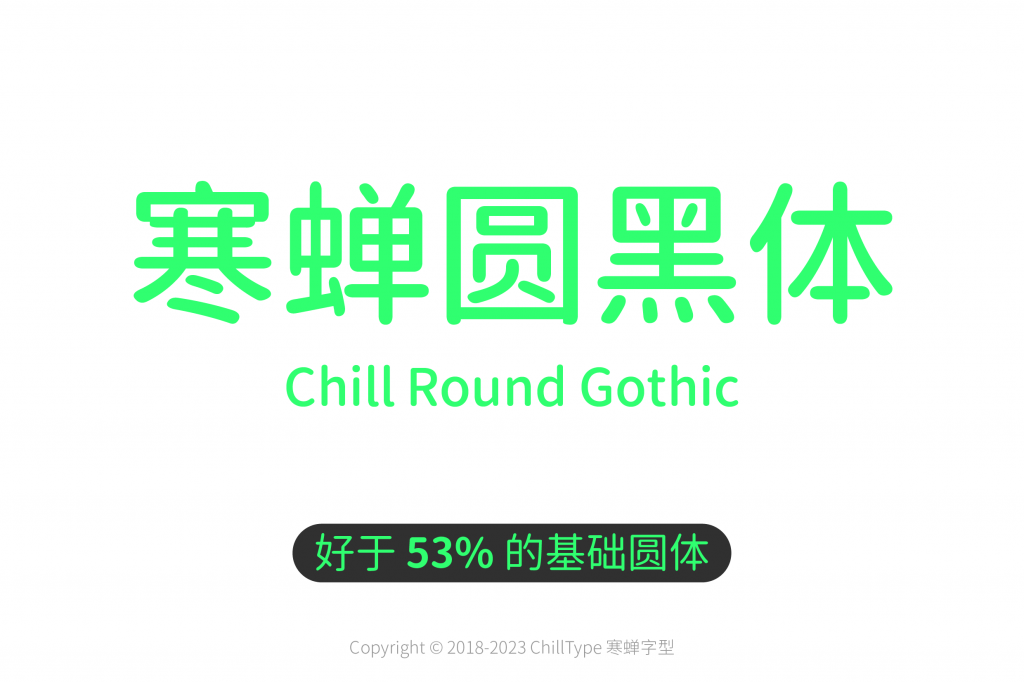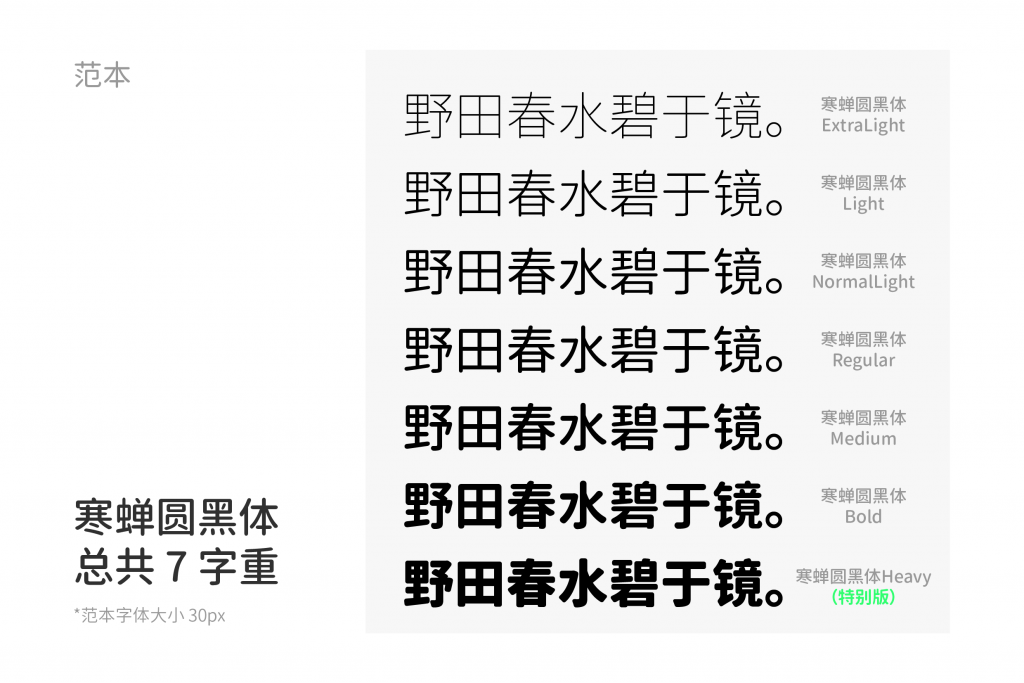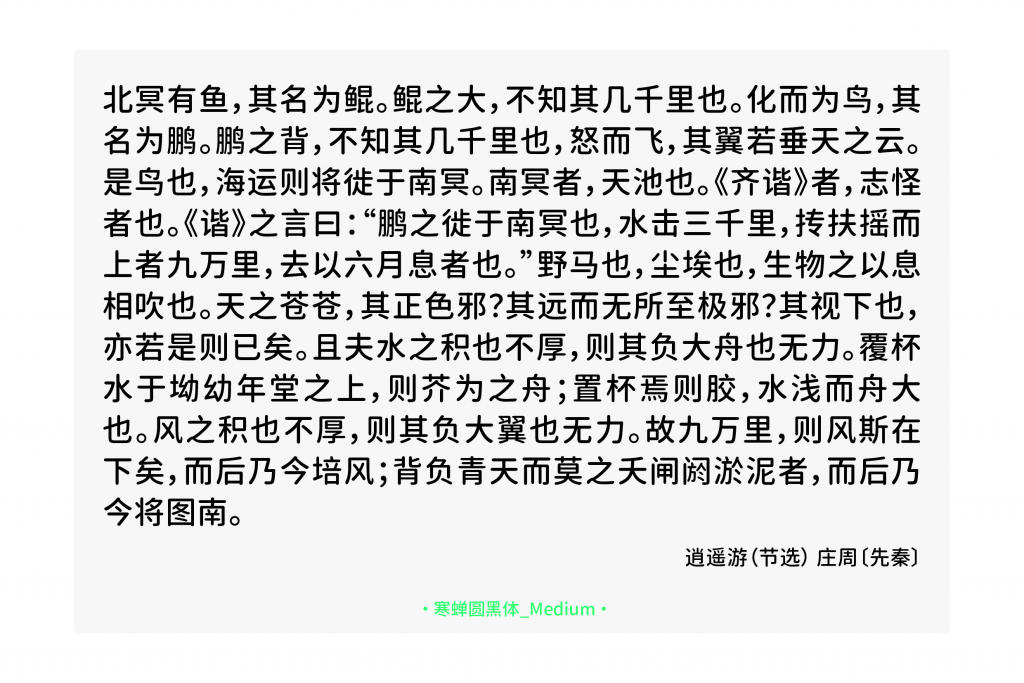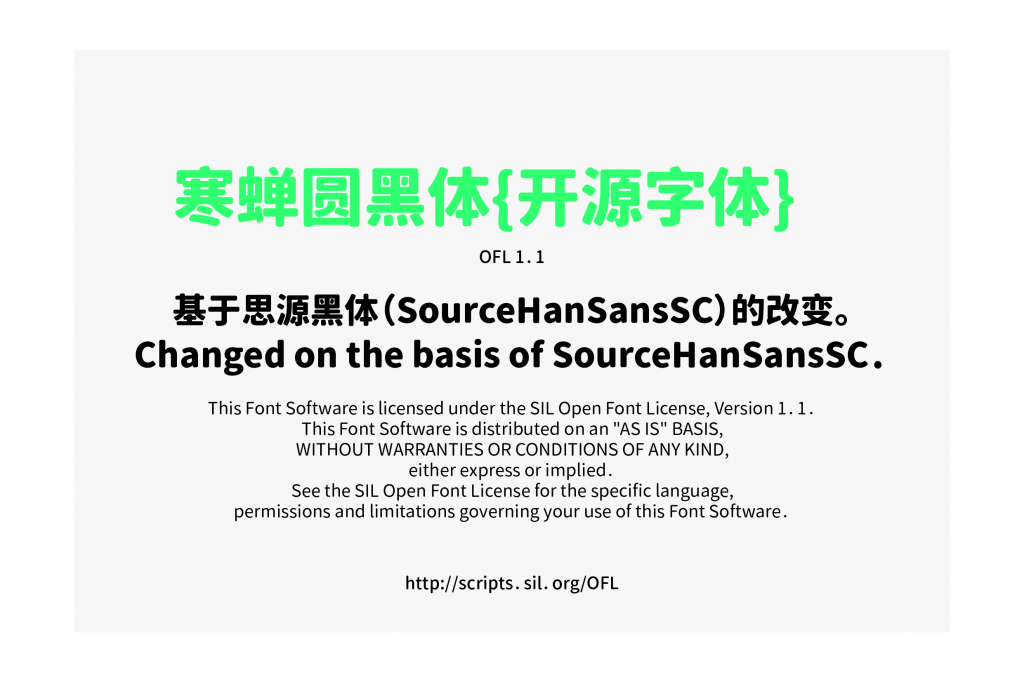
寒蝉圆黑体(Chill Round Gothic)是一款基于思源黑体改造的开源免费商用中文字体。作者通过算法将字形按照一定比例做了圆角处理,又手动校准了 GB2312 字符集中因算法导致的笔画粘连问题。这样既可以保留传统黑体清晰易读的优势,又可以弱化其冷硬感,使字体呈现出圆体该有的柔和感,阅读起来更加舒适。
寒蝉圆黑体提供 ExtraLight、Light、Regular、Medium、Bold、Heavy 在内的 7 种字重,可以覆盖从标题到正文的多种排版需求。比如公众号、PPT、电子书的正文排版;海报、UI 界面、Banner 的标题设计等。